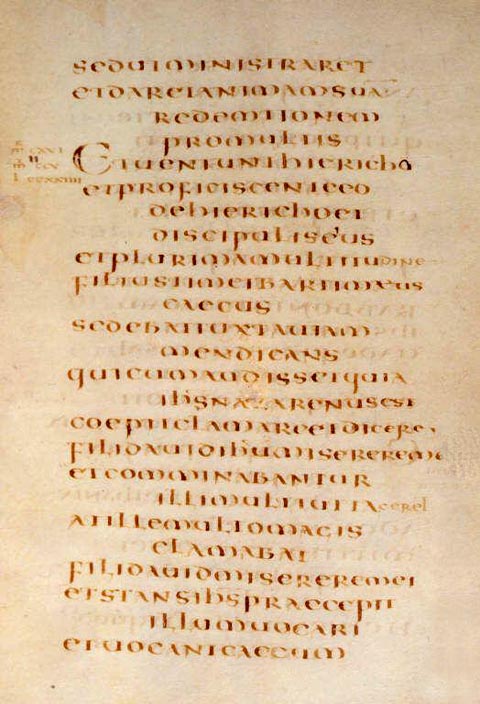
Iniciais e capitulares (I)As letras no início de uma parte dum texto, além do seu valor estético e decorativo, articulam as divisões do texto, organizando os conteúdos.
Capitular, uma palavra portuguesa/espanhola, significa «uma letra no início de um texto». Uma inicial pode ter a altura de várias linhas de texto, o seu corpo sendo substancialmente maior que o do texto corrido. Em manuscritos medievais, algumas iniciais abrangiam o tamanho de uma página inteira. OrigemAs iniciais e as letrinas assumem uma parte importante na decoração e organização dos livros antigos manuscritos e impressos. A partir dos códices, aparece «o livro» um produto acabado, definitivo, referenciável, estável, merecedor de preservação e perenidade. O texto, já não distribuido ao longo de um rolo, mas compostas em páginas, era entendido como uma unidade orgânica, estruturada sintacticamente, semanticamente e por meios gráficos. Em vez de um fluxo interminável de glifos, aparece a separação das palavras, a pontuação, os titulos e as iniciais. O livro torna-se «navegável». A inicial desenvolveu-se nos fins do século VII - a partir das caligrafias praticadas em manuscritos e particularmente a partir da versal do século IX. Em documentos carolíngios é comum vermos maiúsculas romanas, do estilo da Capitalis Quadrata, a servir de iniciais a textos escritos na minúscula carolina. As letras iniciais não são pois uma inovação da iluminura medieval; existiram muito antes. Sendo uma das mais antigas formas de decoração e organização dos textos, desenvolvem-se até alcançar um estatuto primordial na iluminura medieval.
A inicial ornamentada aparece a partir de 650 n.E. A letra inicial será dotada de uma expressão quase mágica. Decorada com toda a espécie de personagens, ela possui a sua própria expressão, podendo ser posicionada no fólio onde adquira uma projecção máxima e dimensões surpreendentes.
Distinguimos diferentes formas de iniciais.
No período românico as iniciais adquirem uma grande variedade, indo da simples letra-silhueta executada a vermelho-azul-verde ornamentadas com troncos de folhagem elegante (littera florata) até formas que sugerem um relevo, em que as letras modeladas se destacam sobre um fundo colorido deixando projectada a sua sombra. Os monstros e os dragões são motivos muito apreciados. Estas bestas fantásticas são utilizadas como elementos decorativos: a sua forma adquire o traçado da letra. O simbolismo e a fantasia adquirem grande significado no período românico. A partir de finais do séc. XIII, as iniciais vão caracterizar-se por uma decoração com elementos vegetalistas (folhas, flores, ramagens entrelaçadas) sobre fundos geralmente coloridos ou dourados (letras filigranadas). Continuação deste tema: Parte II LinksGlossário (em inglês) dos manuscritos iluminados prodigi.bl.uk/illcat/glossary.asp BibliografiaJ.J.G. Alexander: Initialen aus großen Handschriften, München 1978, Prestel Verlag, ISBN 3791304402